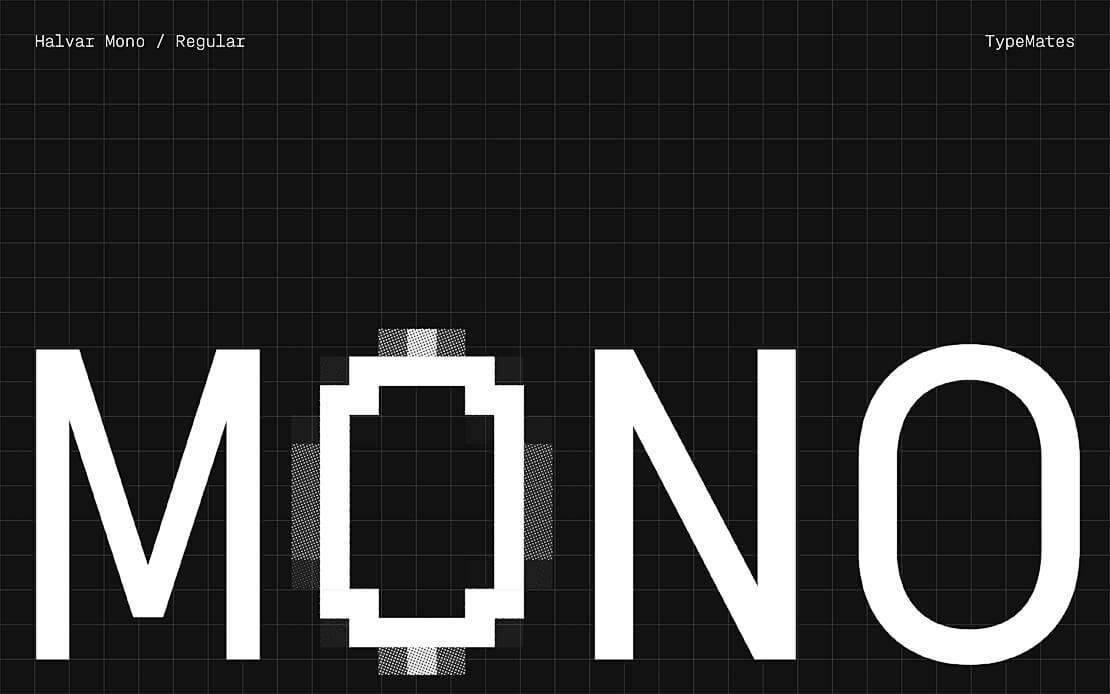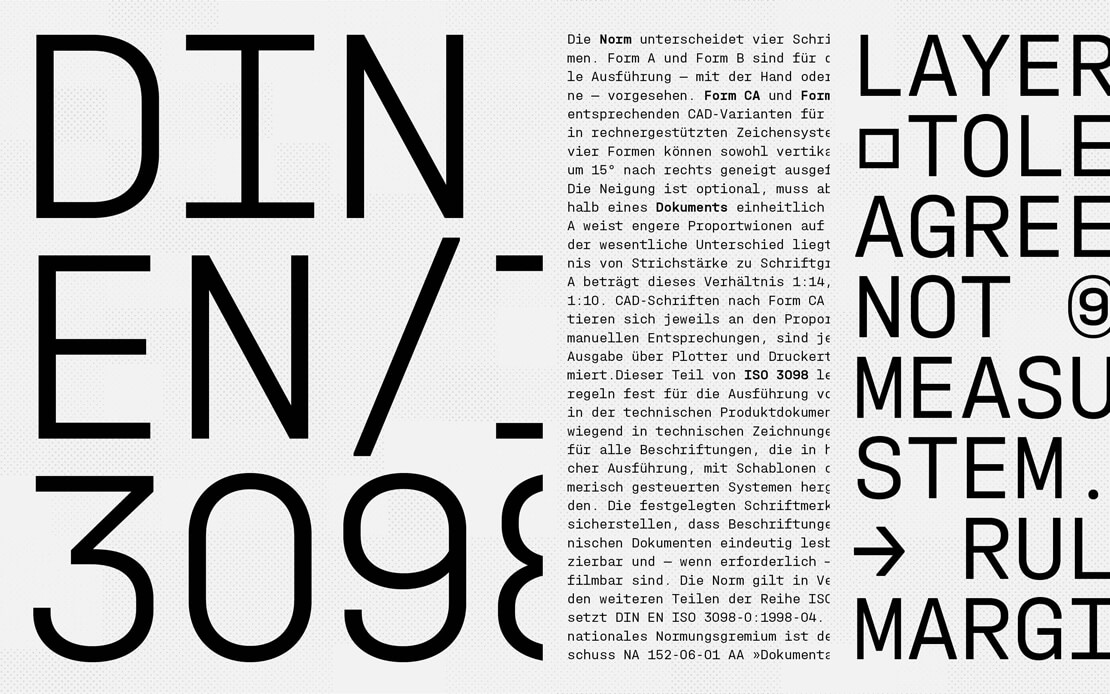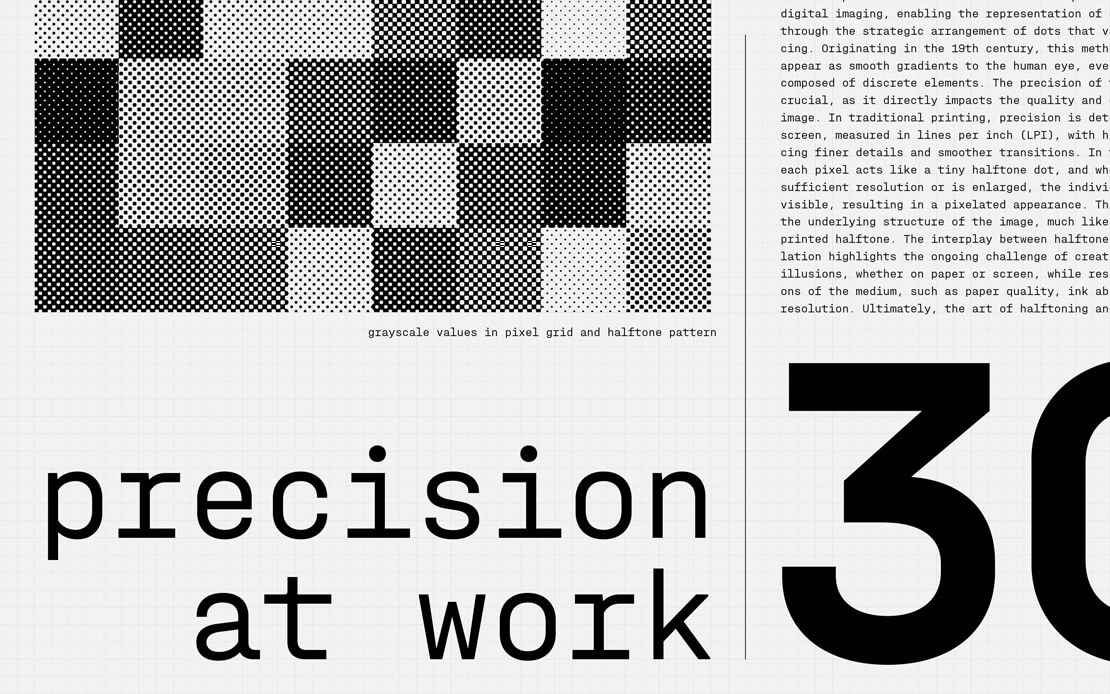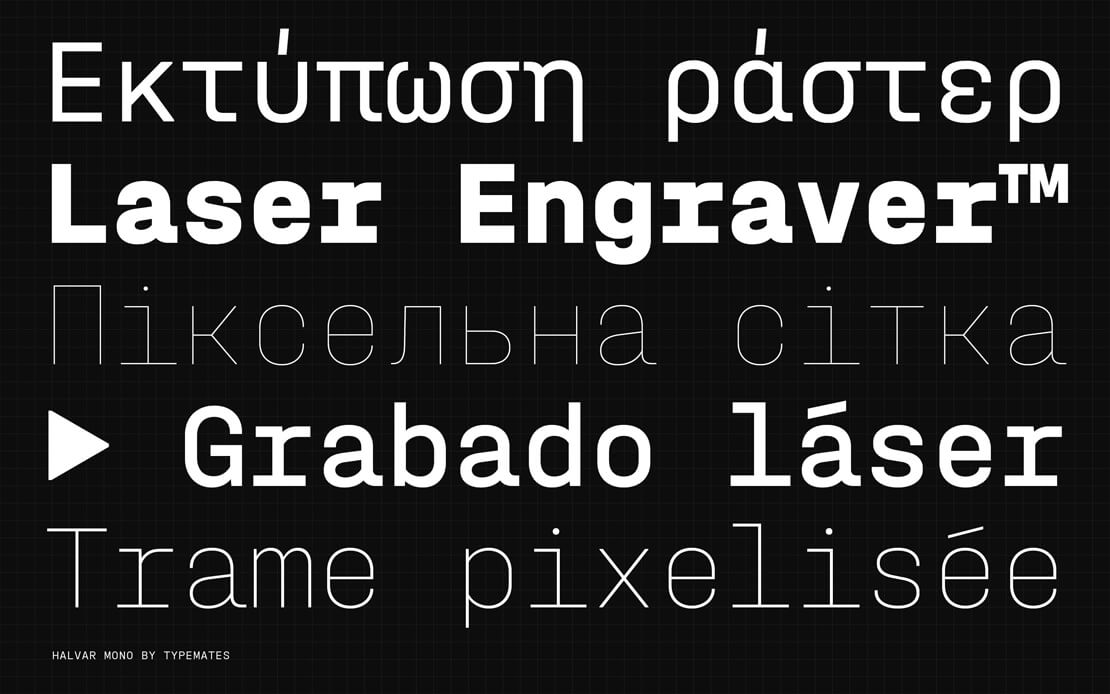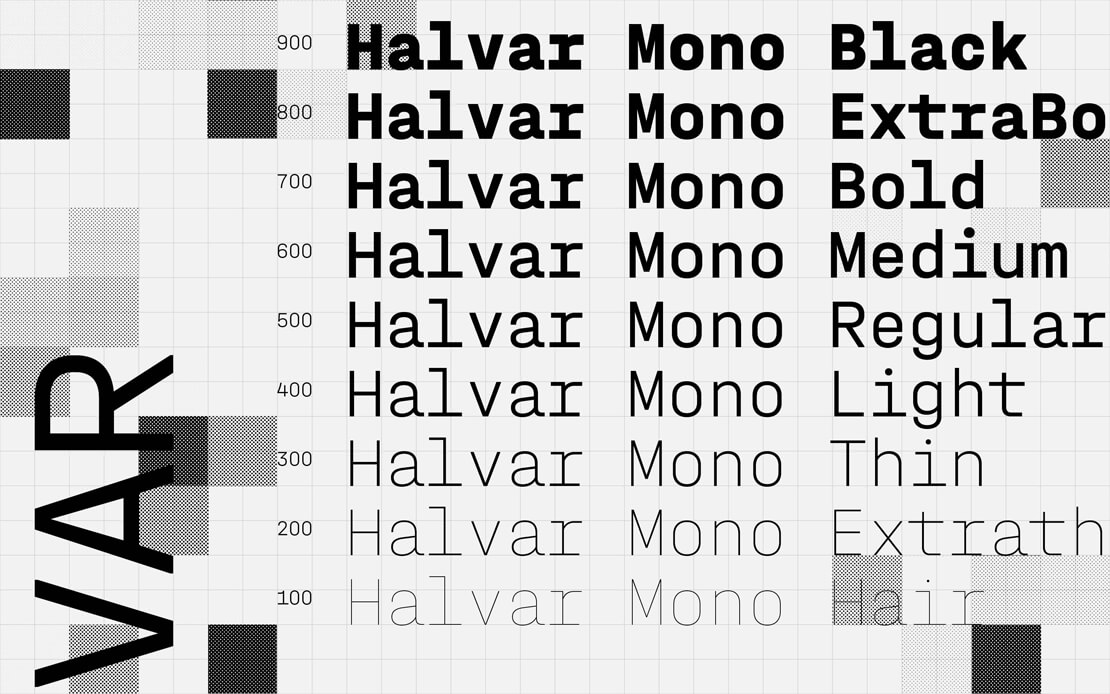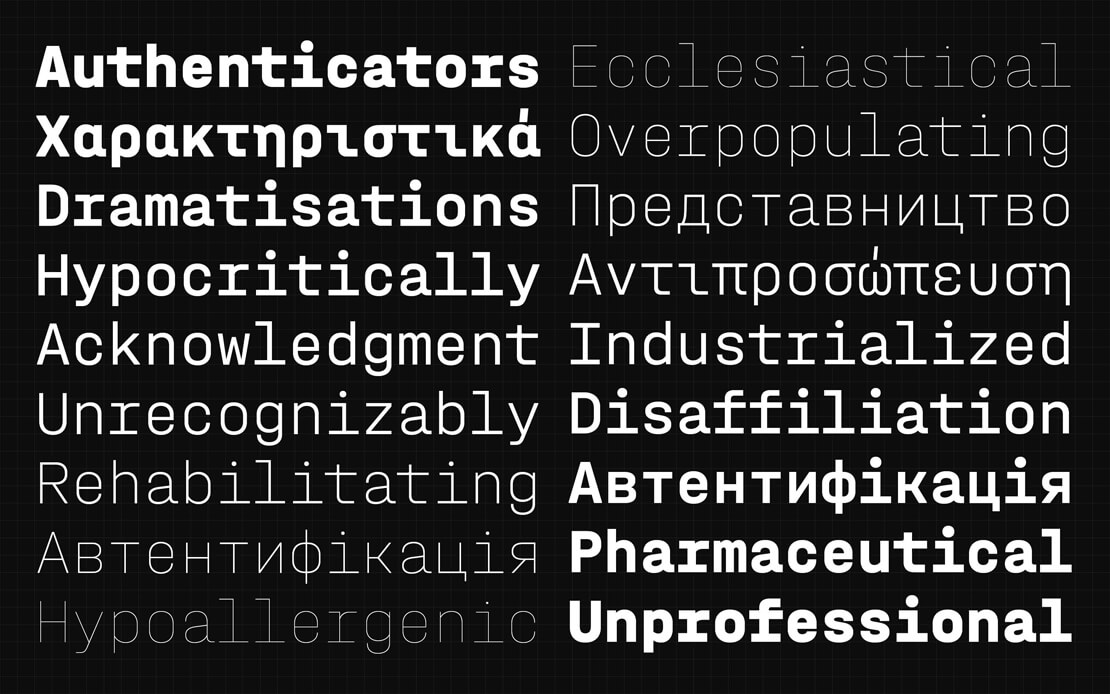
»Halvar Mono« bei TypeMates erschienen
Die Foundry TypeMates erweitert die bestehende Halvar-Schriftfamilie um eine Monospaced-Variante. Die »Halvar Mono« überführt den industriellen Charakter der Ursprungsschrift in ein rasterbasiertes Design.
Feste Breiten und maschinelle Präzision: Mit der Halvar Mono präsentiert das Design-Trio Jakob Runge, Lisa Fischbach und Nils Thomsen-Habermann einen Neuzugang für die typografische Arbeit mit Daten, Tabellen und Code. Der Entwurf behält den pragmatischen Charme der Halvar-Familie bei, setzt jedoch jede Glyphe auf denselben Kegel. Dadurch entsteht ein einheitliches, funktionales Schriftbild, das sich das sogenannte Duplex-Prinzip zunutze macht.
Optimiert für Screen und Interface Design
Um eine hohe Darstellungsqualität auf Bildschirmen zu gewährleisten, ist die Schriftfamilie technisch umfangreich ausgestattet. Ein manuelles TrueType-Hinting, eine großzügige x-Höhe sowie ein robustes Grunddesign sorgen für Stabilität in digitalen Anwendungen.
Zusätzlich zu den Standardschnitten bietet die Halvar Mono verschiedene alternative Zeichen und Stilvarianten. So lässt sich das Schriftbild bei Bedarf auf eine schlichte, reduzierte Form umstellen. Eine weitere integrierte Version wurde speziell für den Einsatz in kleinen Graden und für komplexe Interface-Designs optimiert. Verschiedene Ziffernsätze – darunter Bruch- und hochgestellte Ziffern – runden die typografische Werkzeugkiste für den Mengensatz und technische Layouts ab.
Im Hinblick auf globale Markenauftritte und plattformübergreifende Systeme unterstützt der Zeichensatz der Halvar Mono rund 190 Sprachen. Neben dem lateinischen Alphabet umfasst der Font auch griechische und kyrillische Zeichen. Um die landesspezifischen und kulturellen Sehgewohnheiten exakt abzubilden, wurden diese Zeichensysteme in enger Abstimmung mit Muttersprachlern entwickelt.